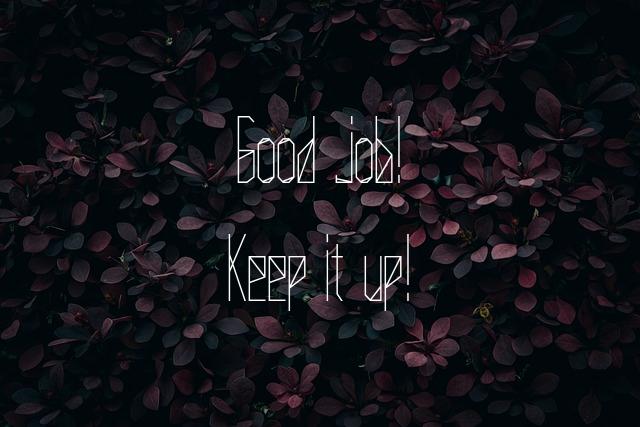
CROOKED 폰트는 Greenegg에서 제작한 독특하고 장식체 감성을 담은 폰트입니다. 영문 폰트로 강렬하고 개성 있는 디자인을 자랑합니다.
CROOKED은(는)
장식 스타일, 별모양/패턴 계열의 생김새를 가지고 있으며
로고 디자인, 포스터, 디지털 광고 등에서 자주 활용되며, 효과적인 메시지 전달에 적합합니다.
이 폰트는 광고/마케팅, 패션/뷰티, 엔터테인먼트 분야에 잘 어울리며,
세련된, 창의적인, 강렬한 느낌을 담고 있는 것이 특징입니다.
이 폰트와 유사한 폰트로는 Futura, Helvetica Neue, Gotham 등이 있어요. 함께 비교해 보시면 좋습니다!